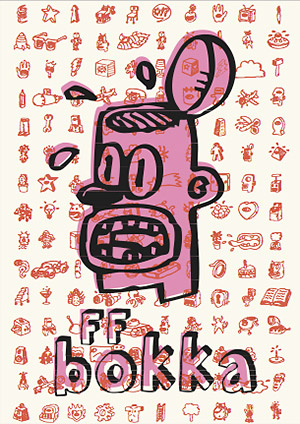
Sammelkarte: Bokka di BaccoEine Fontcard vom Oktober 1997, gestaltet von John Critchley. Sie
zeigt die 3D-Blockbuchstabenschrift FF Bokka, die Critchley gemeinsam mit
Darren Raven entwarf. Spaßige Ergänzung zur Schriftfamilie waren rund
sind beeinflusst von Fernsehen, Comics und Pop-Kultur. Raven studierte bis 1996
an der Staffordshire University Design und Animation. Danach legte er am Royal
College of Art in London sein Master of Arts ab. Zusammen mit dem
FontFont-Designer John Critchley entstanden die zu den Karikaturen passenden
handgezeichneten Blockbuchstaben in vier verschiedenen Ausführungen:
gefüllt, konturiert, dreidimensional und schattiert.